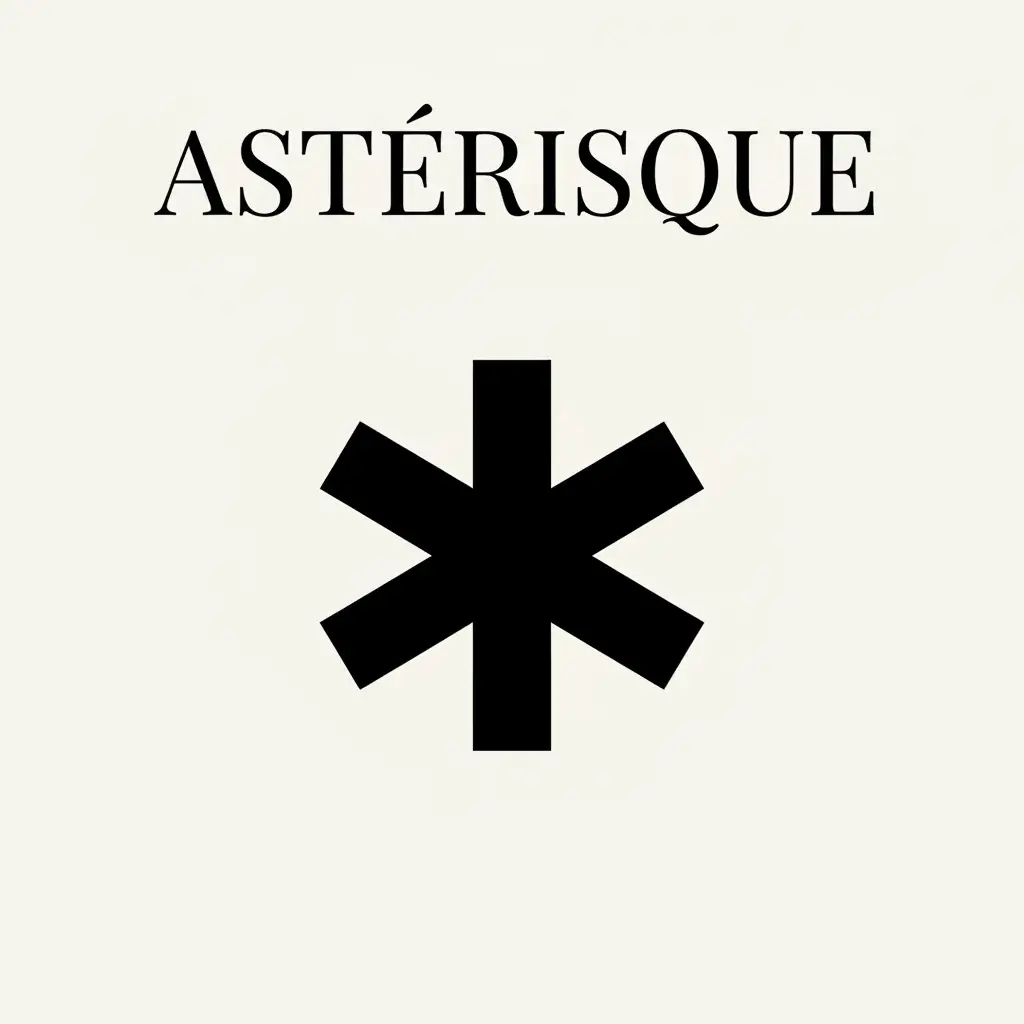
Astérisque | Définition & utilisation
Un astérisque, dont le symbole est une étoile (*), est un signe typographique voué à différentes fonctions.
- signaler un renvoi ou un appel de note
- Sont concernées uniquement les substances issues de la liste des médicaments essentiels*.
- Cette toponymie ne concerne que les odonymes*.
- introduire le renvoi ou l’appel de note
- * La liste des médicaments essentiels est disponible sur notre site web.
- * Nom propre des voies de communication.
- masquer un nom propre
- La plaignante, Madame A*******, souhaite faire appel de cette décision.
- préciser l’agrammaticalité d’une forme
- Le pluriel *des chevals est une forme récurrente chez les jeunes scripteurs.
Véritable vedette des contrats d’assurance, l’astérisque s’utilise généralement pour éviter d’alourdir un texte. Toutefois, certaines informations introduites par un ou plusieurs astérisques sont loin d’être des considérations inutiles.
Une petite étoile qui a décidément bien des choses à cacher…
L’astérisque ou l’art de la dissimulation
Signe typographique, l’astérisque peut indiquer l’absence de caractères ou d’informations complémentaires. Toujours en exposant (en haut, à droite), il se place tout de suite après le mot, sans espace typographique. Toutefois, en règle générale, il est suivi d’une espace insécable.
Difficile d’imaginer qu’une petite étoile puisse dissimuler bien des choses ? Véritable roi de l’anonymat, l’astérisque — et surtout les mentions auxquelles il renvoie — n’a pourtant pas fini de vous en mettre plein la vue…
Astérisque : le renvoi ou l’appel de note
Tout document écrit peut présenter des notes de bas de page. Du roman au catalogue, de l’écrit administratif à la littérature scientifique, ces notes, à l’intention du lecteur, permettent de mentionner des informations complémentaires qui, autrement, surchargeraient le texte.
Ces indications sont aussi appelées renvois lorsqu’elles font référence à une source, dans le cas de données chiffrées par exemple, à un auteur, en lui attribuant la paternité d’une citation ou d’une notion, ou encore à un autre passage du même ouvrage.
- Un taux d’inflation galopant à plus de 30 %* a poussé les consommateurs à vivre à crédit, et ce, même pour satisfaire les plus essentiels de leurs besoins.
* Insee, « Évolution de l’indice des prix à la consommation », février 2018.
- Nous considérons, à l’image du père de la discipline, que la linguistique ne peut être que sociolinguistique*.
* William Labov, Social Stratification of English in New York City, 1966.
- Cette hypothèse a déjà fait l’objet d’une démonstration exhaustive* et nous nous emploierons dans le prochain chapitre à poursuivre ces considérations préétablies.
* Voir Chapitre 4 : La réflection contre la réflexion : le prisme social du XXIe siècle.
L’appel de note désigne l’astérisque, le symbole à proprement parler. Il est placé après le mot et renvoie le lecteur à la note placée, elle, en bas de page, en fin de chapitre ou en fin de volume. Par ailleurs, lorsque l’ouvrage comporte de nombreuses notes, l’astérisque est remplacé par un chiffre.
Si la fonction de ces notes permet transparence et précision dans les communications scientifiques, ce n’est pas forcément le cas de certains documents administratifs. Dans les contrats, l’astérisque permet souvent de dissimuler une clause, une condition particulière qui précise une information pourtant essentielle.
- Si vous détenez l’option Âge d’Or, vos petits-enfants célibataires de moins de 25 ans sont également couverts, à condition de voyager avec vous et uniquement pendant la durée du déplacement*.
* Nous nous réservons le droit d’apporter certaines modifications à ces conditions.
- La location comprend une assistance routière 24 h sur 24 h*, un kilométrage illimité** et une réduction de 20 % à la pompe***.
* À l’exclusion des jours chômés (samedi, dimanche et jours fériés).
** Dans les limites du département administratif.
*** Dans les stations-service participantes.
La volonté de dissimulation de ces informations est avant tout typographique, voire physique. En effet, ces notes des bas de page sont souvent écrites en petits caractères à la fin du document. Pour apporter davantage de confusion, des suites de plusieurs astérisques, difficiles à compter, brouillent la lecture des différents renvois.
Astérisque est un nom commun masculin, issu du latin asteriscus, signifiant « petite étoile ».
Paronyme du célèbre personnage de bande dessinée, il s’en distingue toutefois phonétiquement : Astérix [asteʁiks] et astérisque [asteʁisk] ne partagent pas la même finale phonétique.
Astérisque : l’anonymisation du nom propre
Fort heureusement, le rôle de dissimulation de l’astérisque n’est pas toujours dédié à l’abus du consommateur. Cette petite étoile s’avère, au contraire, très efficace pour protéger la vie privée, et en particulier l’anonymat des victimes.
Ainsi, dans les écrits juridiques, judiciaires ou journalistiques, il est d’usage de masquer, totalement ou en partie, un nom propre pour empêcher la divulgation d’informations personnelles et confidentielles, tenues au secret professionnel.
- Dans le procès-verbal du témoin oculaire, il est fait mention que Hugo B***** déclare avoir vu l’assaillant sortir son arme et faire feu.
- Judith D******, qui a tenu à conserver son anonymat, nous confie sensiblement la même histoire à leur sujet.
- Rappelons, Madame la Juge, que la plaignante, Madame *******, a porté plainte à cinq reprises avant la survenue des faits.
Dans un contexte nettement moins formel, l’astérisque peut également servir à masquer une insulte. Il permet ainsi d’euphémiser des jurons et des mots considérés comme vulgaires ou grossiers.
Astérisque : l’agrammaticalité d’une forme
Par convention, l’astérisque est également utilisé dans le domaine de la linguistique pour signifier qu’une forme est agrammaticale, autrement dit, incorrecte d’un point de vue grammatical ou syntaxique.
Dans ce cas précis et contrairement aux autres usages de l’astérisque, le symbole est collé au mot qu’il précède. Autrement dit, il n’y a aucune espace typographique entre l’astérisque et la forme agrammaticale.
- La construction *pallier à quelque chose est pourtant utilisée par la grande majorité des locuteurs.
- Le pluriel de travail, travaux, pose un problème sémantique : comment parler de ses différents *travails pour désigner ses diverses expériences professionnelles passées, le tout sans recourir à un synonyme ?
La linguistique s’intéressant à tous les usages de la langue, les linguistes recourent à l’astérisque pour distinguer les formes impossibles, non conformes aux règles internes du langage (*vu hier mon frère j’ai) des formes possibles.
Bon nombre de ces formes possibles correspondent à un certain usage de la langue. Elles répondent aux règles grammaticales (accords, orthographe spécifique, etc.), mais ne peuvent pas être utilisées dans tous les contextes.
Ces formes ne requièrent pas d’astérisque, car elles sont grammaticalement correctes (flic est synonyme de policier dans le registre familier).
Si vous disposez d’un clavier numérique, l’astérisque possède une touche spécifique, marquée de son symbole (*). Il est alors un signe mathématique, celui de la multiplication. Sa mise en exposant, par défaut, en fait le raccourci clavier idéal, malgré sa finalité numérique, et non alphabétique.
Si vous ne disposez que d’un clavier alphabétique, la touche alphanumérique 8 devrait produire le même symbole. Si ce n’était pas le cas, assurez-vous d’appuyer simultanément sur les touches shift et 8 de votre clavier.
Articles coups de cœur
Vous souhaitez en savoir plus sur la poésie, l’orthographe ou les locutions et expressions de la langue française ? Découvrez sans plus attendre notre sélection pour que rédaction rime avec perfection.
Questions fréquentes sur l'astérisque
- Écrit-on un ou une astérisque ?
-
Le mot astérisque est masculin singulier. On écrit toujours un astérisque.
- Il manque un astérisque dans ta note de bas de page.
- La prochaine fois, tu liras les mentions précédées d’un astérisque !